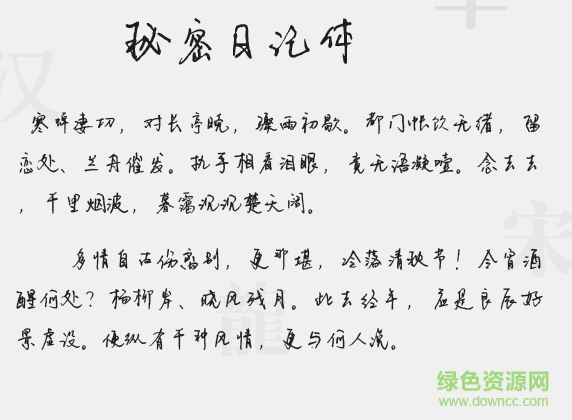
秘密日記體字體頗有一副手寫(xiě)草書(shū)體的氣概,該字體筆畫(huà)隨心所欲行如流水,字里行間能透露出作家的思緒情感,非常好看,歡迎到綠色資源網(wǎng)下載安裝!
秘密日記體是一款適合鋼筆書(shū)法書(shū)寫(xiě)的字體,該字體的誕生,要經(jīng)過(guò)字體設(shè)計(jì)師的創(chuàng)意設(shè)計(jì)、字體制作人員一筆一劃的制作、修改,技術(shù)開(kāi)發(fā)人員對(duì)字符進(jìn)行編碼、添加程序指令、裝庫(kù)、開(kāi)發(fā)安裝程序,測(cè)試人員對(duì)字庫(kù)進(jìn)行校對(duì)、軟件測(cè)試、兼容性測(cè)試,生產(chǎn)部門(mén)對(duì)字庫(kù)進(jìn)行最終產(chǎn)品化和包裝上市!